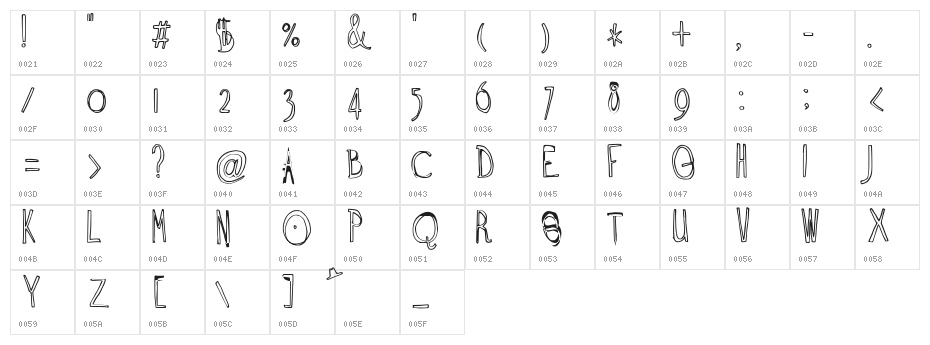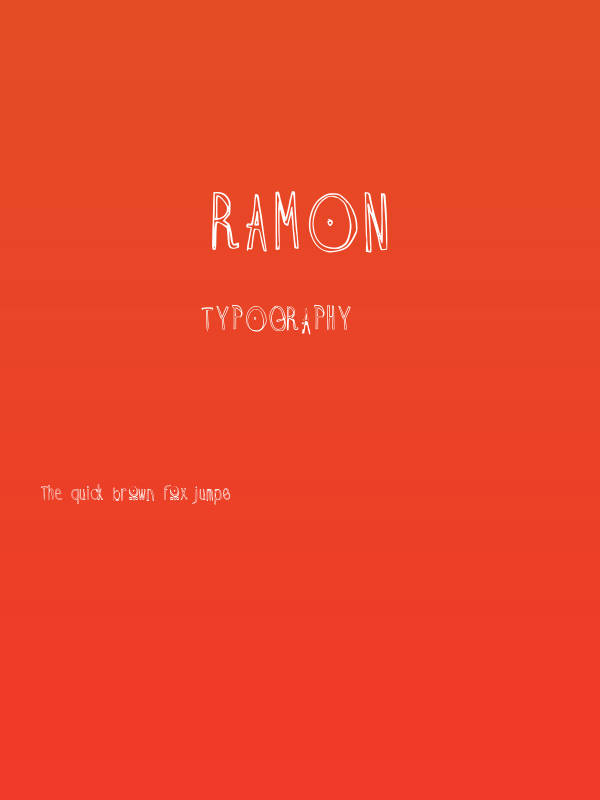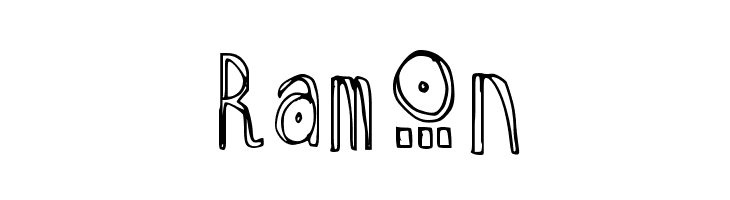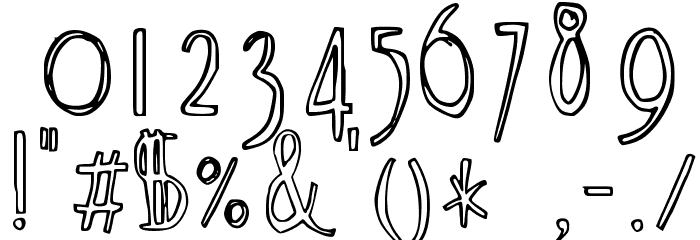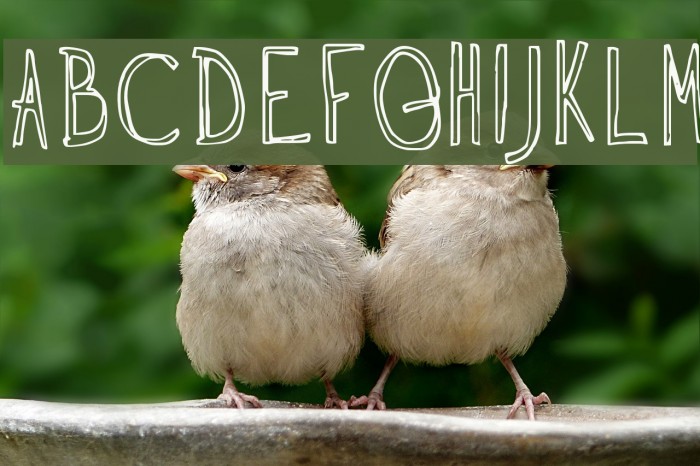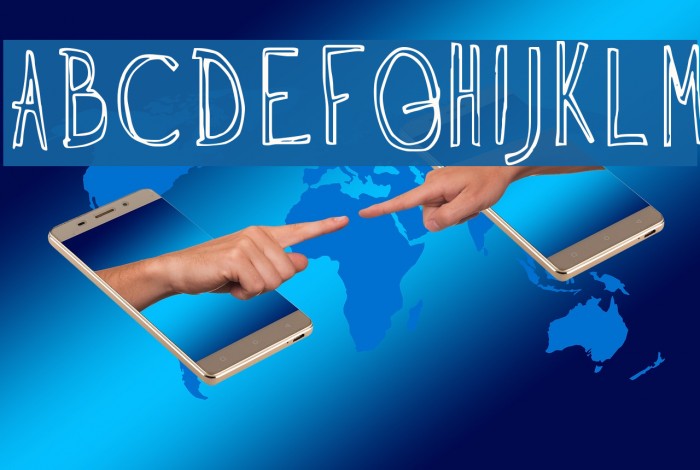
Ramon Font
| Gesamtstil | Whimsical |
| Anwendungsfall | Headlines, Logos, Creative projects |
| Vorgeschlagene Projekte | Ideal for children's books, playful branding, creative posters, and artistic invitations. |